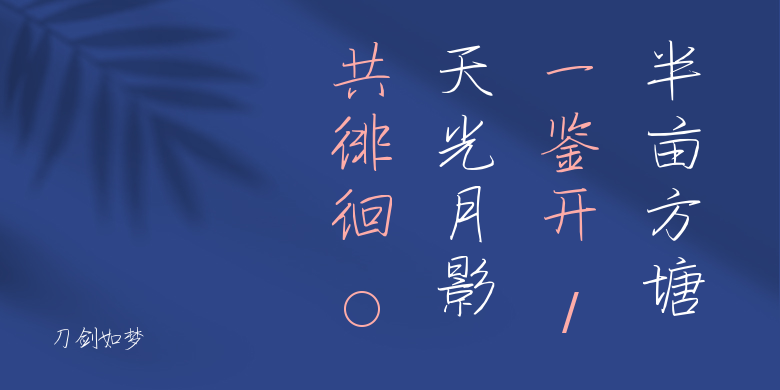
刀剑如梦
刀剑如梦,这款字体结构工整、笔画清晰,兼顾美观与易读性,适用于标题、正文、海报、包装、LOGO 等多种场景。字形优雅稳定,风格百搭耐看,适配日常排版与创意设计,让文字呈现更舒适、更具质感。刀剑如梦一笔一画,皆是细节,以均衡的比例、流畅的线条打造舒适视觉体验,字形端正大气,风格简约现代。无论是商业设计、品牌宣传还是日常排版,都能轻松驾驭,让文字更有格调与力量。刀剑如梦字体下载。